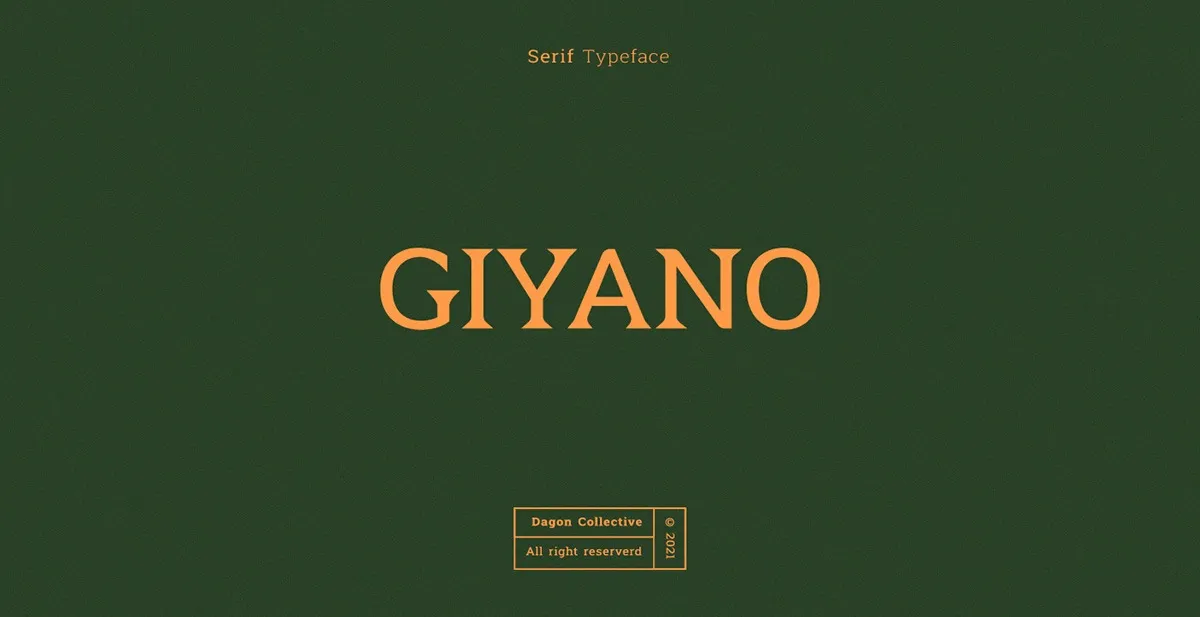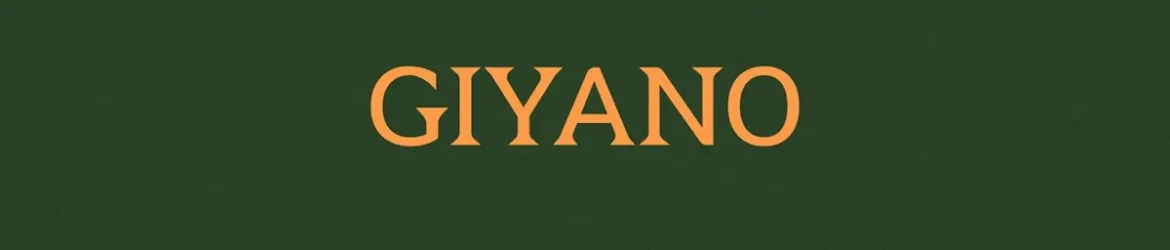
Esta é uma fonte serif inspirada nas artes femininas do século passado. Ela transmite elegância e valor, sendo perfeita para títulos elaborados e estilos criativos de gráficos e design tipográfico. A Giyano Font Family foi especialmente desenvolvida para criar um tom sofisticado e refinado em logomarcas, embalagens, outdoors e outros formatos. Seu risco elegante e personalizado combina perfeitamente com criações modernas que buscam uma identidade única e de alto nível. Inspirada nos movimentos artísticos do passado, essa fonte é uma escolha ideal para quem busca um toque único em seus projetos gráficos.